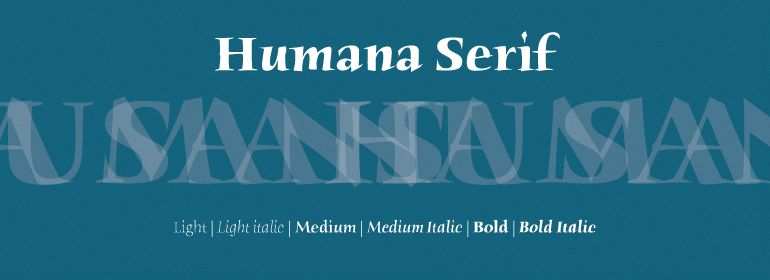
ITC Humana™ Serif
ITC Humana字体是英国设计师Timothy Donaldson的作品。唐纳森首先用一支钢笔创作了ITC Humana Script,然后又设计了相应的罗马体。ITC Humana是任何需要清晰度和个性感的字体的理想选择。
ITC Humana font is the work of British designer Timothy Donaldson, an extended and versatile font family with a large array of variations. Donaldson first created ITC Humana Script with a broad-tipped pen and then went on to design the corresponding roman. ITC Humana is the perfect font for anything requiring both clarity and a touch of personality.